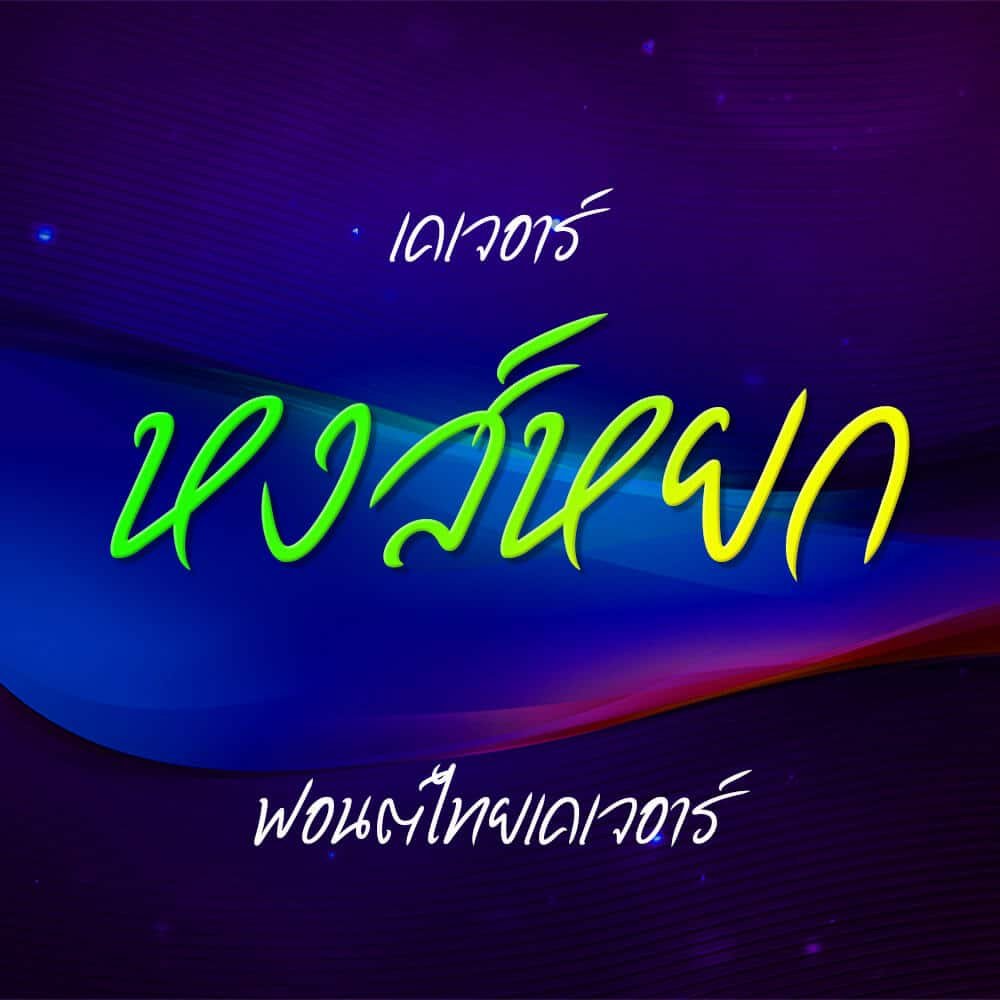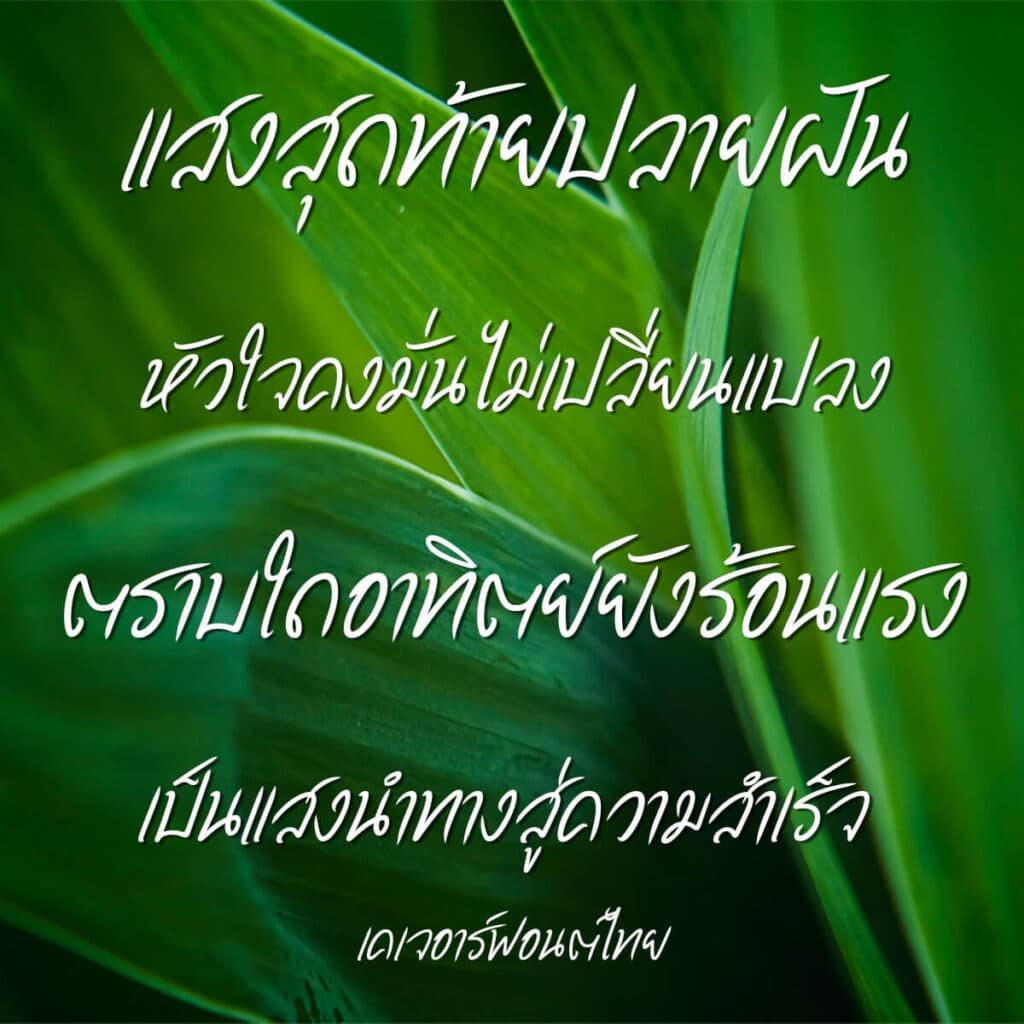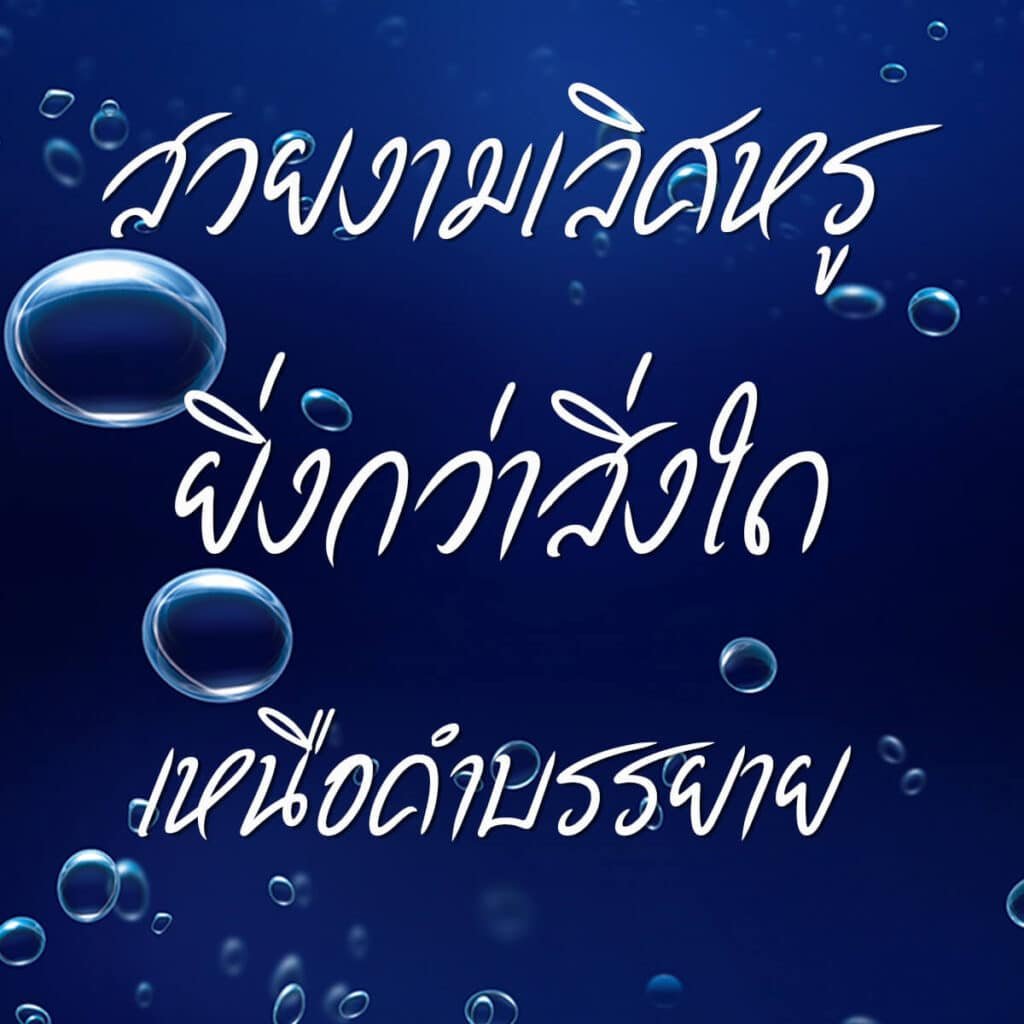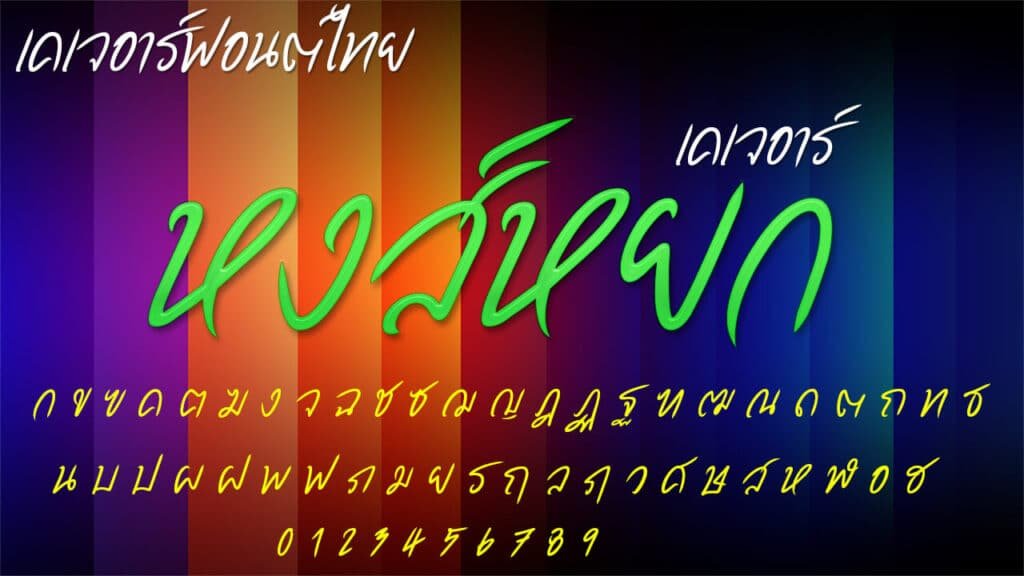
เคเจอาร์ หงส์หยก (KJR HONGYOK)
อีกหนึ่งฟอนต์ลายมือสวยๆ จากค่ายเคเจอาร์ เหมาะแก่การใช้งานหลากหลายแนว ฟอนต์ที่แจกนี้เป็นเพียงตัวทดลองให้ใช้นะครับ มีติดบั๊กหลายตัว ต้องขออภัยครับสนใจฟอนต์เวอร์ชันเต็ม ติดต่อสั่งซื้อได้ครับ